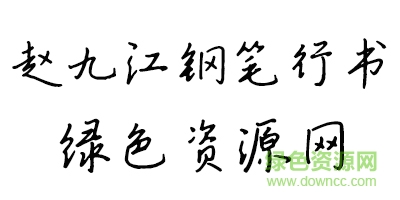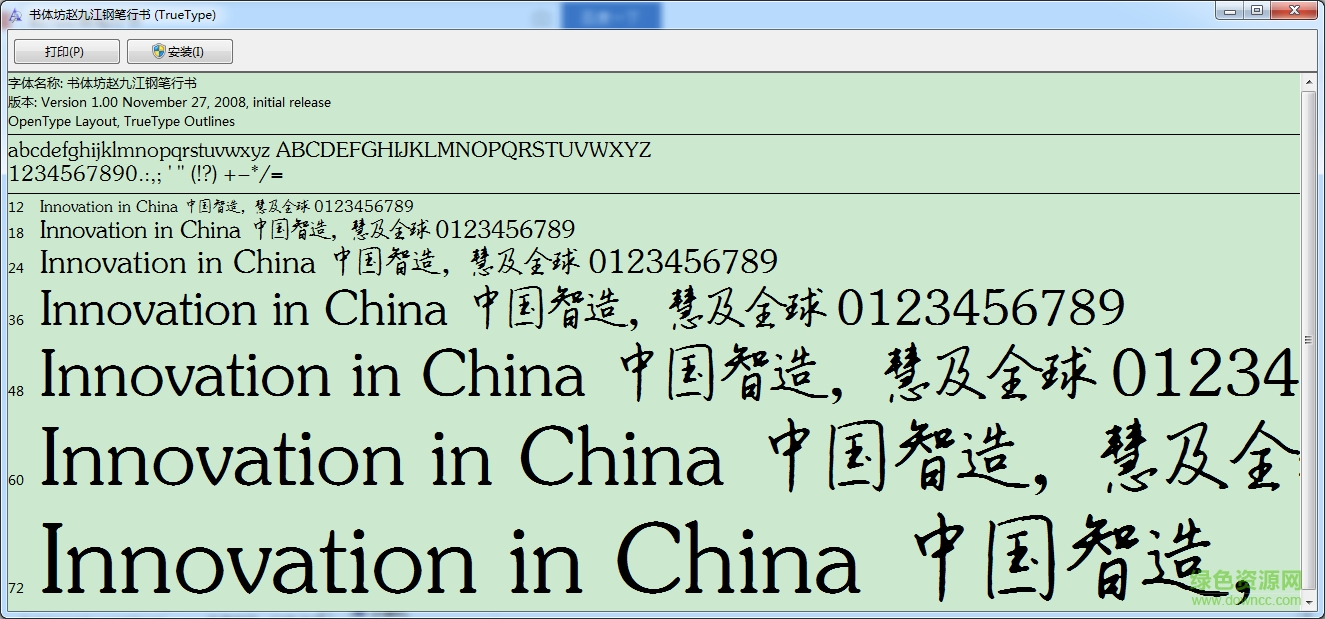
書體坊趙九江鋼筆行書字體
趙九江鋼筆行書字體是一款經(jīng)典的鋼筆行書字體,這款字體筆畫細(xì)膩,粗細(xì)均勻,字形優(yōu)美,非常適用于廣告設(shè)計(jì),平面設(shè)計(jì)等領(lǐng)域,感興趣的朋友歡迎來綠色資源網(wǎng)下載使用!
趙九江鋼筆行書字體效果展示
趙九江鋼筆行書字體